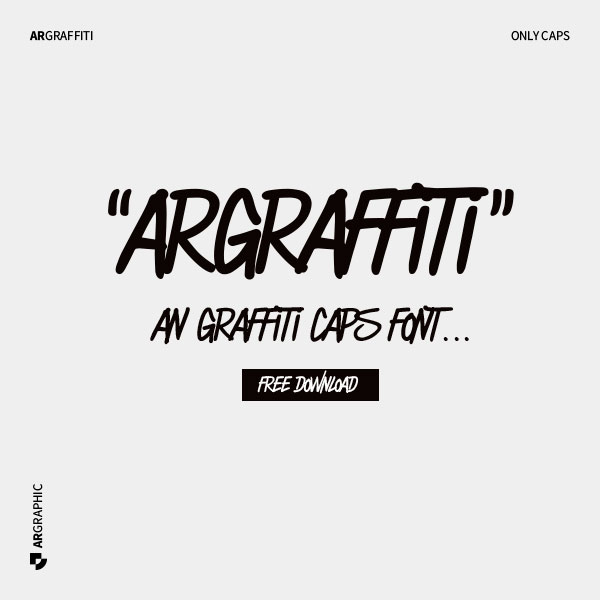
La typographie joue un rôle essentiel dans la conception graphique, et l’une des options qui attirent l’attention est la font Argraffiti. Cette font en lettres capitales allie l’élégance de la typographie classique à l’énergie et à l’audace du street art. Avec ses traits, ses angles marqués et son allure puissante, la typographie Argraffiti offre un impact visuel saisissant qui captive instantanément le regard.
Les Caractéristiques de la font Argraffiti
La font Argraffiti se distingue par ses lettres capitales audacieuses, évoquant l’écriture de graffiti sur les murs des villes. Ses traits épais et ses angles vifs lui confèrent une présence visuelle unique et une impression de mouvement dynamique. Chaque lettre est conçue avec une attention minutieuse pour capturer l’énergie et l’expressivité du street art. L’utilisation de la typographie Argraffiti dans vos créations peut aider à transmettre un sentiment de rebelle, d’aventure et de modernité.
Utilisations créatives de la font Argraffiti
La typographie Argraffiti offre de nombreuses possibilités créatives pour les concepteurs graphiques. Elle est souvent utilisée dans les affiches, les logos, les en-têtes de sites web et les bannières publicitaires, où elle attire immédiatement l’attention. Son style audacieux est particulièrement efficace pour promouvoir des marques et des événements destinés à un public jeune et branché. Les artistes, les musiciens et les entreprises liées à la culture urbaine peuvent également tirer parti de cette typographie pour renforcer leur identité visuelle et communiquer leur esprit rebelle et novateur.
Créer une identité visuelle forte avec la font Argraffiti
L’Argraffiti est bien plus qu’une simple typographie, c’est un moyen de créer une identité visuelle distinctive pour votre marque ou votre contenu. Son apparence unique et artistique vous permet de vous démarquer et de susciter la curiosité des utilisateurs. En associant votre marque à l’Argraffiti, vous créez une expérience visuelle cohérente et mémorable, renforçant ainsi votre présence en ligne.
Font Argraffiti : Une typographie gratuite pour une créativité illimitée
Argraffiti, créée par l’agence Argraphic, est mise à votre disposition gratuitement, ce qui ouvre de nouvelles perspectives créatives pour votre contenu. Que vous soyez un rédacteur SEO, un concepteur graphique ou un passionné de design, l’utilisation d’Argraffiti vous permettra de transformer votre texte en une œuvre d’art typographique. Avec cette typographie captivante à portée de main, votre créativité n’a plus de limites. Téléchargez Argraffiti dès maintenant et donnez une nouvelle vie à votre contenu grâce à cette typographie unique et gratuite.
La font Argraffiti est une typographie puissante pour les concepteurs graphiques.
Créé par l’agence de création design Argraphic, la typographie Argraffiti est une option puissante pour les concepteurs graphiques qui souhaitent créer des visuels percutants et captivants. Son mélange unique de typographie classique et de style graffiti offre une combinaison d’élégance et d’audace qui attire immédiatement l’attention. Bien qu’elle puisse ne pas avoir d’impact direct sur le référencement, elle peut contribuer à améliorer l’expérience utilisateur et l’engagement, ce qui peut indirectement avoir des avantages pour votre site web en termes de trafic organique et de partage social. Explorez les possibilités créatives de la typographie Argraffiti et laissez-la donner vie à votre contenu avec son impact visuel saisissant.